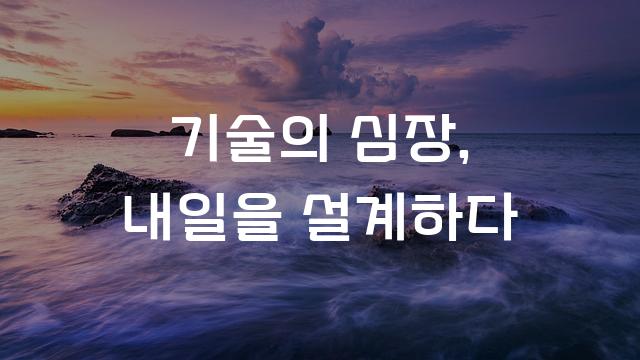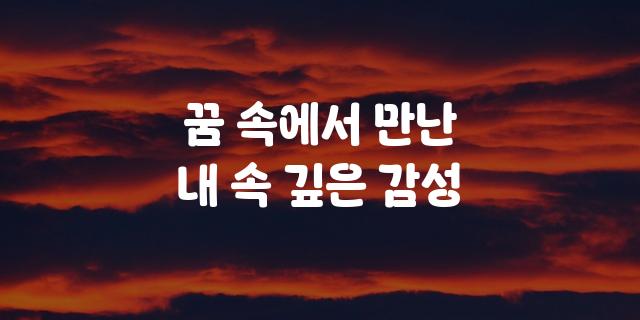
구미돋움체는 깔끔하고 현대적인 고딕 디자인을 지닌 문서용 폰트입니다. 모던하면서도 기본적인 고딕 스타일로, 다양한 문서 작성에 최적화되어 있습니다.
구미돋움체은(는)
기본 고딕, 감성적인, 부드러움 계열의 생김새를 가지고 있으며
웹/앱 디자인, 보고서/문서 등에서 자주 활용되며, 효과적인 메시지 전달에 적합합니다.
이 폰트는 크리에이티브, 기술/IT 분야에 잘 어울리며,
현대적, 명확한 느낌을 담고 있는 것이 특징입니다.